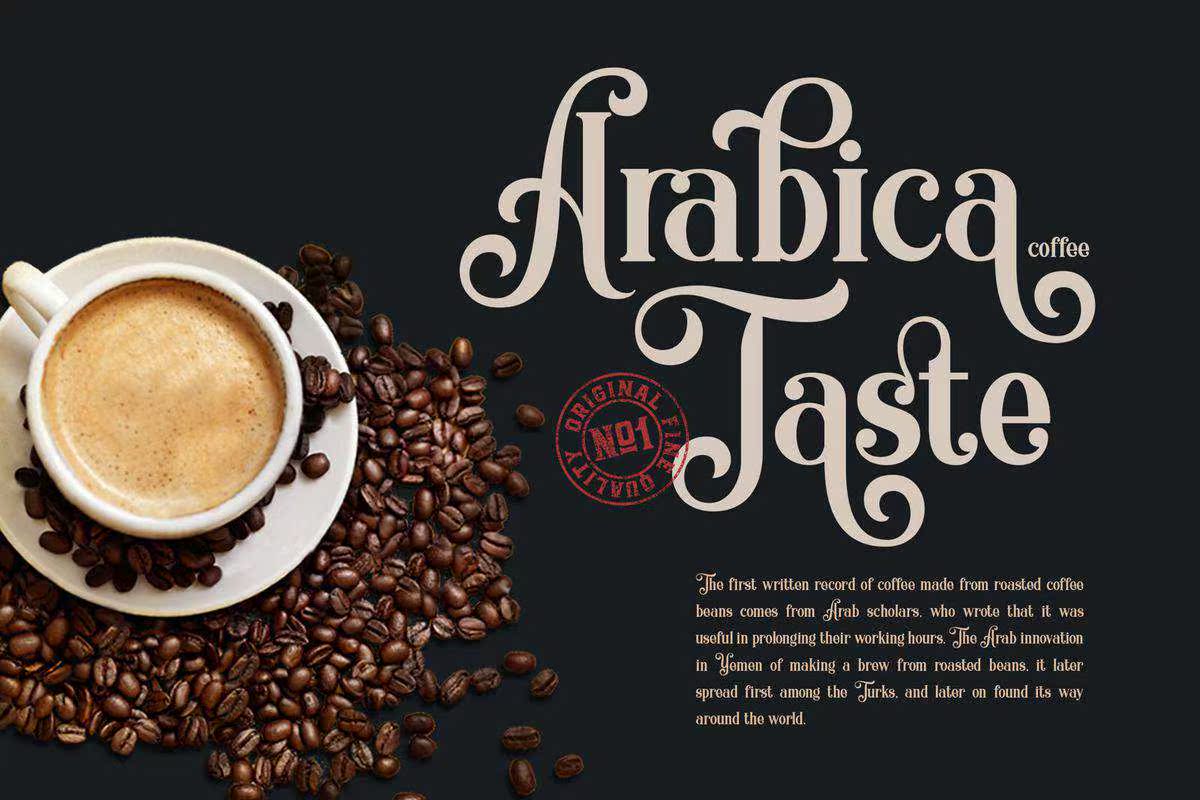
Quiskai-SaniqueseRiffont,I将统一的大写字母组合在一起,并添加一种可选字符和一个自动字符,Quiskah具有300多个字形。您可以使用图标、徽章、字体、包装、标题、海报、t恤/服装、问候卡和婚礼宣传。您可以将Quiskaw与可选字符混合并匹配,以适合您的项目。Quiskai-SaniqueseRiffont,我将唯一的大写字母和某种替代字符与自动冲水、Quiskawave 300多个字形相结合。您可以使用图标、徽章、字体艺术、包装、标题、海报、t恤/服装、问候卡和婚礼宣传。您可以将Quiskawa与替代字符混合搭配,以配合您的项目。